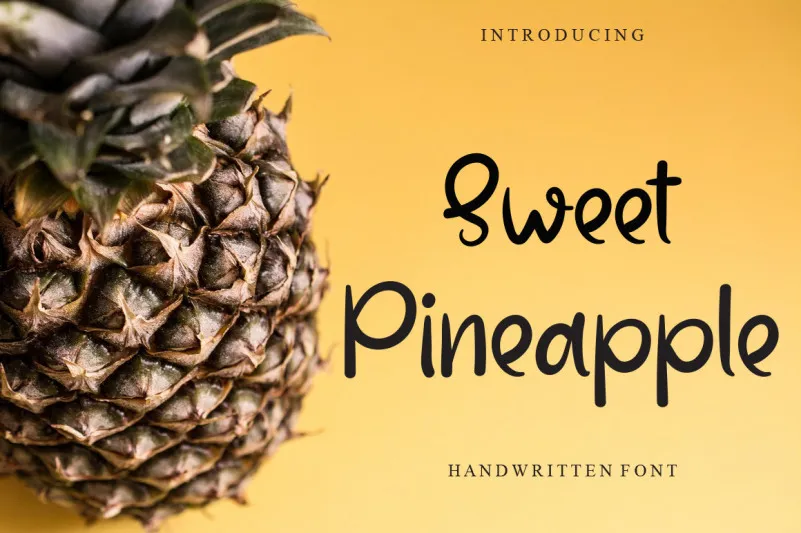
Esta é uma fonte desenhada a mão com um toque delicado e amigável. Seu estilo natural e único faz dele um recurso perfeito para uma ampla variedade de projetos gráficos, desde cartões de felicitações até ilustrações infantis. Suas linhas suaves, seus traços desencontrados e sua personalidade fofa enriquecem qualquer design, limitado apenas pela criatividade do seu pensamento. Ideal para quem busca uma fonte que combina perfeitamente com o amor pela natureza e a simplicidade das plantas. Perfeito para designers de gráficos em diversos campos, desde arte infantil até ilustrações urbanas. A Sweet Pineapple Font se destaca como um recurso amigável, versátil e encantador que permite ao designer criar uma variedade incrível de projetos com apenas sua imaginação!